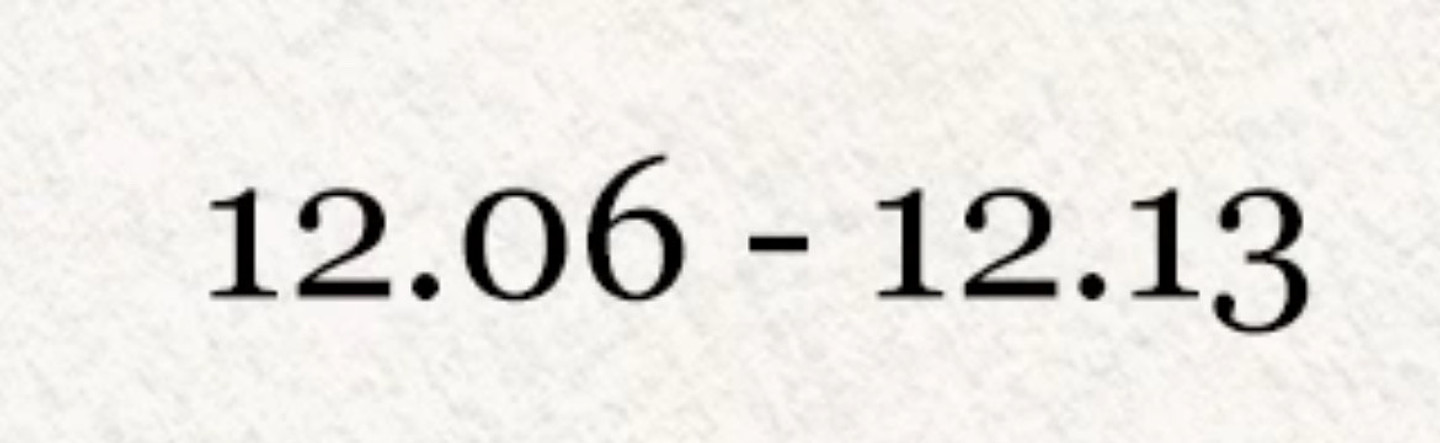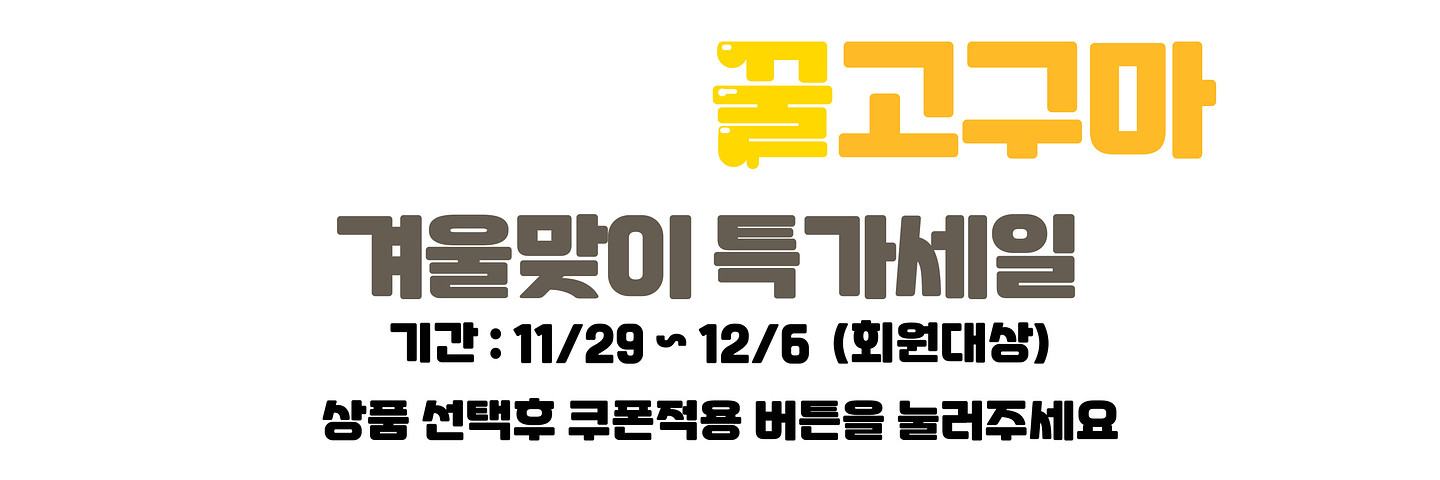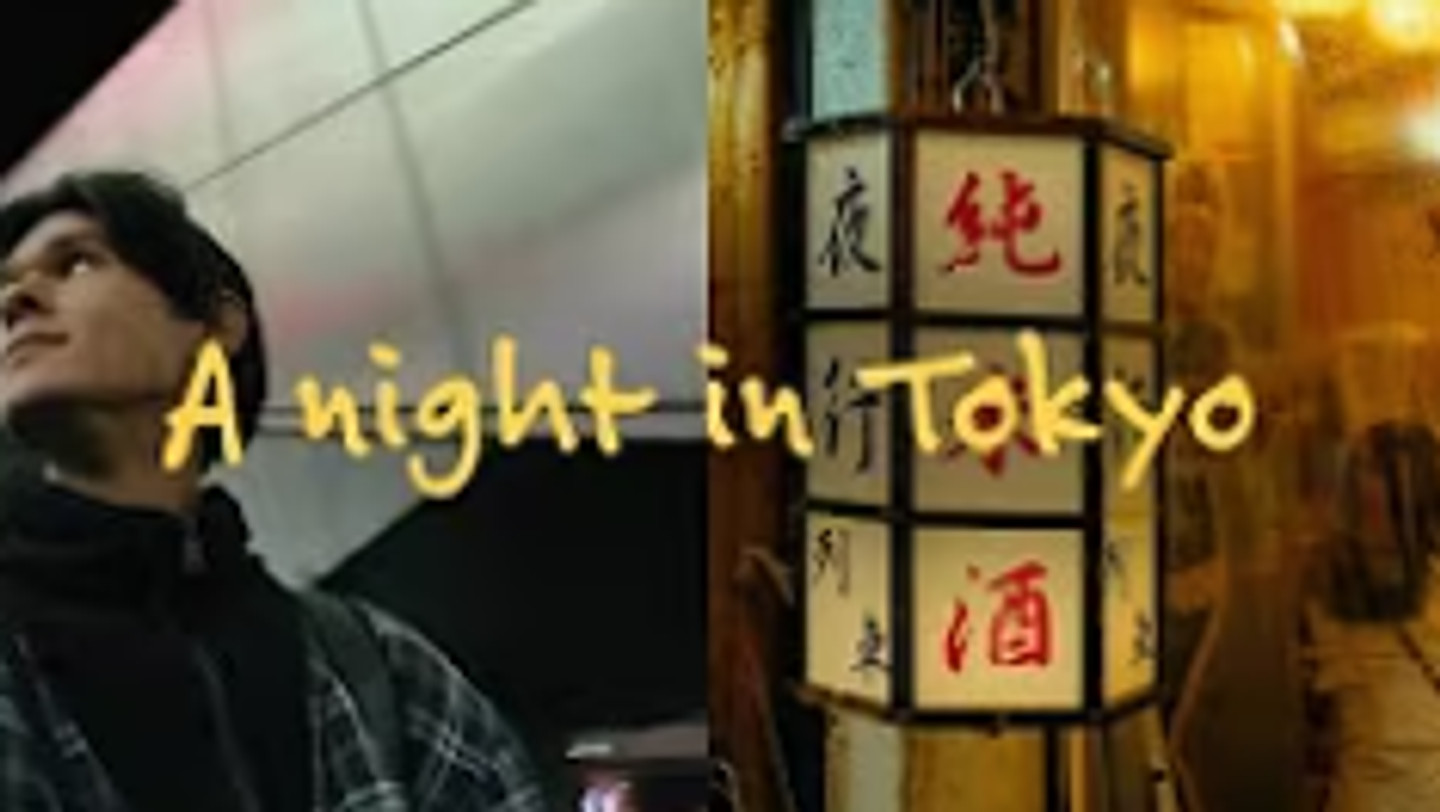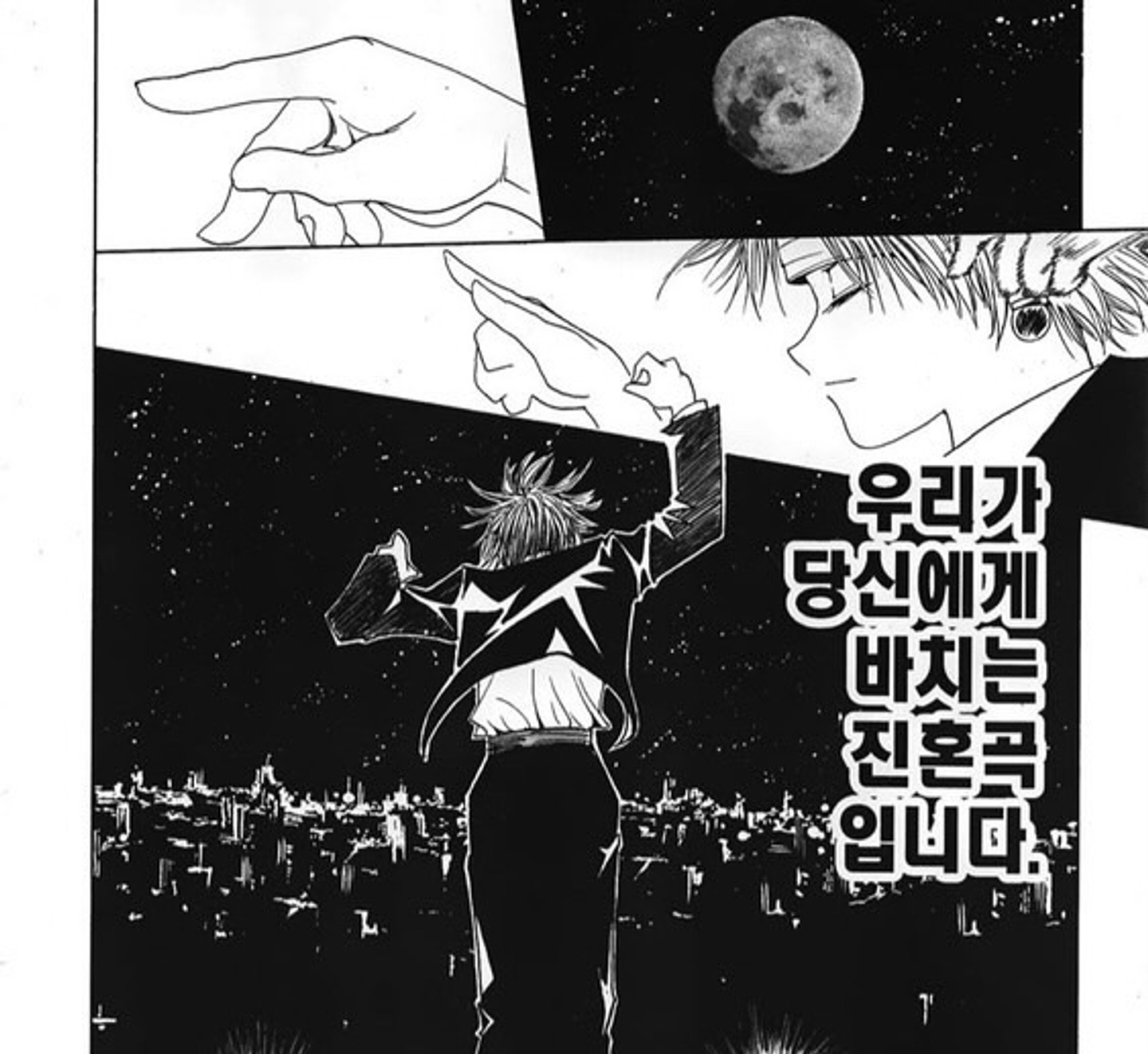
이런만화폰트이름이먼가교…?
이 폰트 아시는 분?
이폰트 뭔지 아시나요? 없다면 비슷한폰트라도 있을까요?ㅜ
이거 서체 뭘까요 어비폰트같아서 찾아보는데 잘 모르겠네요.. 감사합니다
기아 티니핑 콜라보 유니폼 마킹 폰트 뭔가요? 이름부분말고 숫자부분이요!
도와주세요...
안뇽하세요 이거 무슨 폰트인지 알려주실 수 있을까요?
이게 손으로 그린듯한 이애프도 그린듯한건지...무슨폰트인가요?
이게 무슨폰트인가요?
ㅅ와 ㅈ이 특이한데, 산토끼체는 아닌거 같아요 ㅠ 도저히 모르겠어서 질문합니다.
무슨 폰트인지 부탁드립니다
영문 폰트 뭔지 알 수 있을까요? 작업자가 안알려줘서 수배합니다.
이 폰트 알려주세요
앞글자만 살짝 크게 나오는 영어 폰트뭔지 알수 있을까요?
폰트 수배합니다!
또또 채널 폰트 궁금해요!
이 폰트 뭘까요ㅠㅠㅠㅠ 아무리 찾아도 안나와요ㅠㅠㅠ
고수님들 이 서체 무슨 서체인가요???
이서윤체 치고는 가로가 아닌 세로로 납작한 거 같은데 이서윤 폰체가 맞나요..? 맞다면 어떻게 저런식으로 했을까요 제가 쓰면 더 가로로 납작해지는 거 같은데 ㅜㅜ
이 폰트 궁금해요
카카오톡에 있었던 글씨인데 없어져서요. 무슨 폰트 일까요...?
얼불춤 메스머라이저에 나오는 폰트입니다 찾아도 뭔지 모르겠어요
무슨 폰트죠???
말풍선 안에 들어있는 폰트 어떤걸까요 ㅜㅜ
뭘까요
이폰트 뭔가요?
멀까요
무엇일까욤
무슨 폰트일까용..?
무슨 폰트일까용ㅜㅜ
무슨폰트죠??
이 폰트가 어떤 폰트인지 아시는 분 있나요?
'믿을 구석' 부분의 서체가 궁금합니다!
무슨폰ㄴ트죠`??~?!?
인스타에서 봤는데 무슨폰트일까요? 이거랑 비슷한 갤럭시폰에서 사용 가능한 폰트도 있을까요?
미리캠퍼스 ai에서 만든건데 위에 있는 거 폰트가 뭘까요 ?
이형범치과가 어떤 폰트인지 알 수 있을까요?
이니스프리 팝업스토어에 쓰인 이 폰트, 딱 제가 원하는 느낌인데 무엇일까요?
무슨폰트인지 알고싶습니다. 살짝 변형해서 사용한거같은데 기준이되는 폰트가 궁금합니다.
폰트 알려주세요ㅜ
폰트 뭔가용 ㅠ
이 폰트 어디서 쓸수있나요?? 이폰트로 썸네일 만들고 싶어서 물어봅니다!
폰트 뭘까요?...
이폰트뭘까요
못찾겠어요 도와주세요...ㅠㅠ 픽셀로 보이는 건 깨져서 그런거고 원래는 매끈한 느낌입니다!
눈에 많이 익은 듯하면서도 이름이 안 떠오르는데 무슨 폰트일까요 😳
인스타 현진님 글씨체인데 너무 예뻐서 비슷한 글꼴을 찾고 싶어요ㅠㅠ!!
해당 영문 폰트, 무슨 폰트일까요? 꼭 찾고 싶습니다..!!